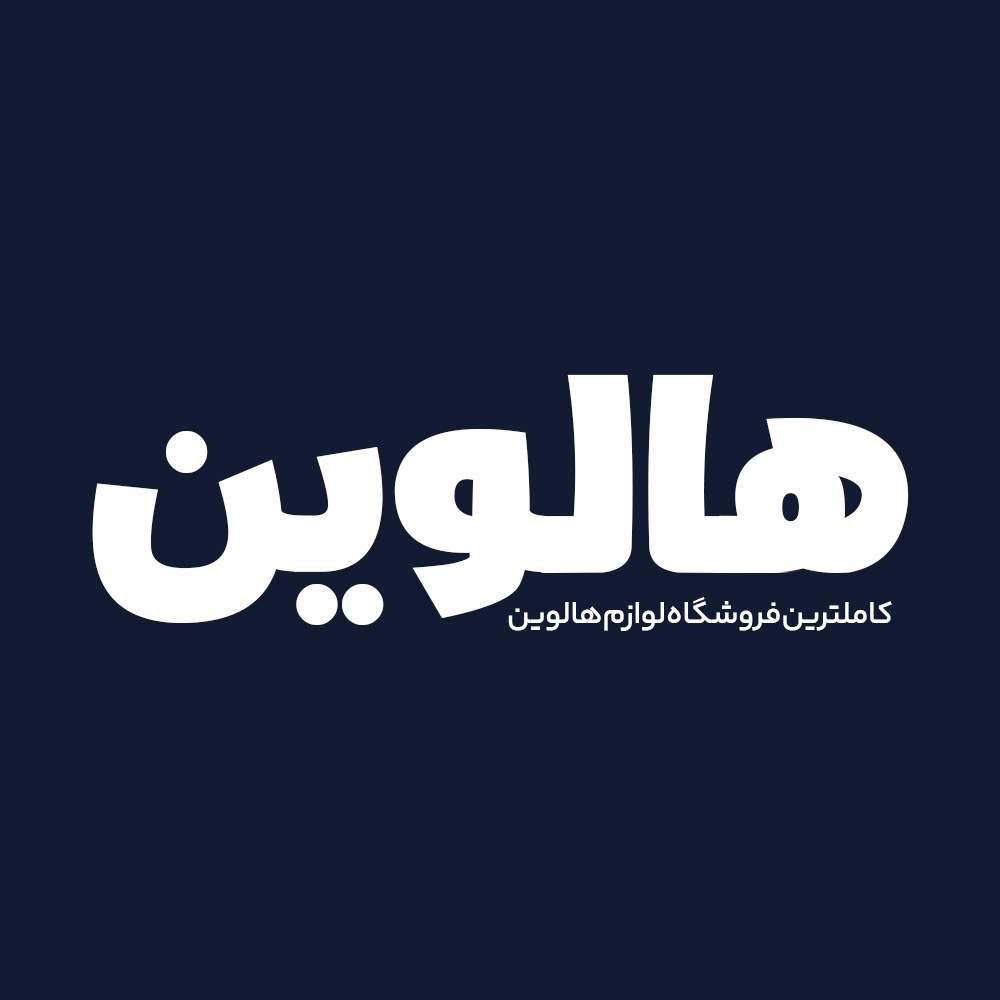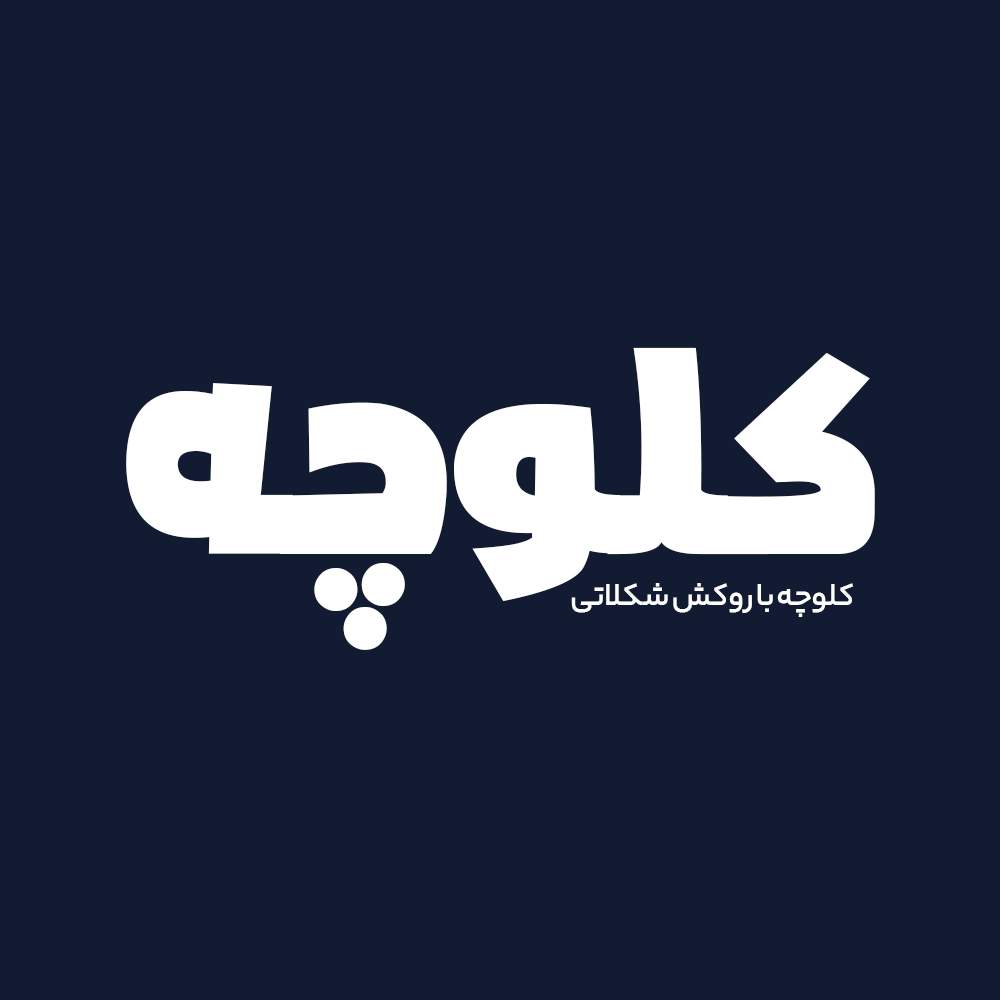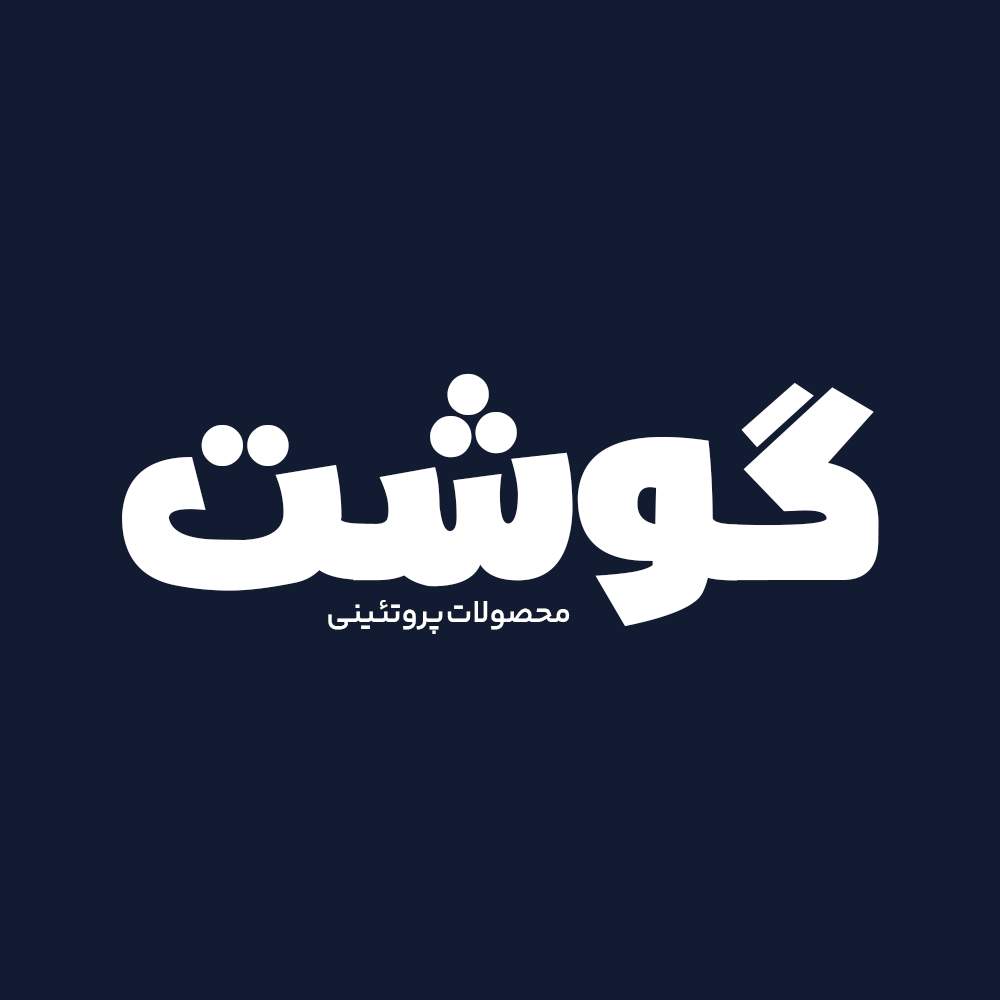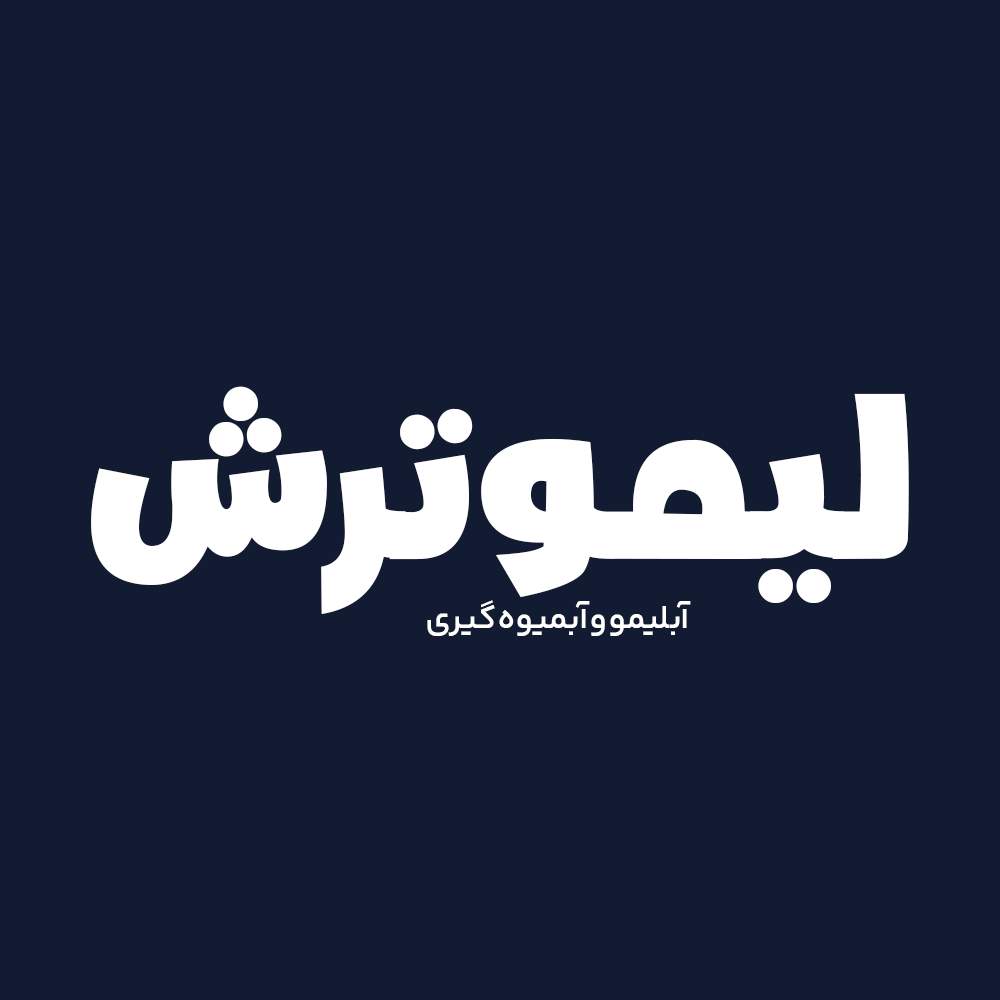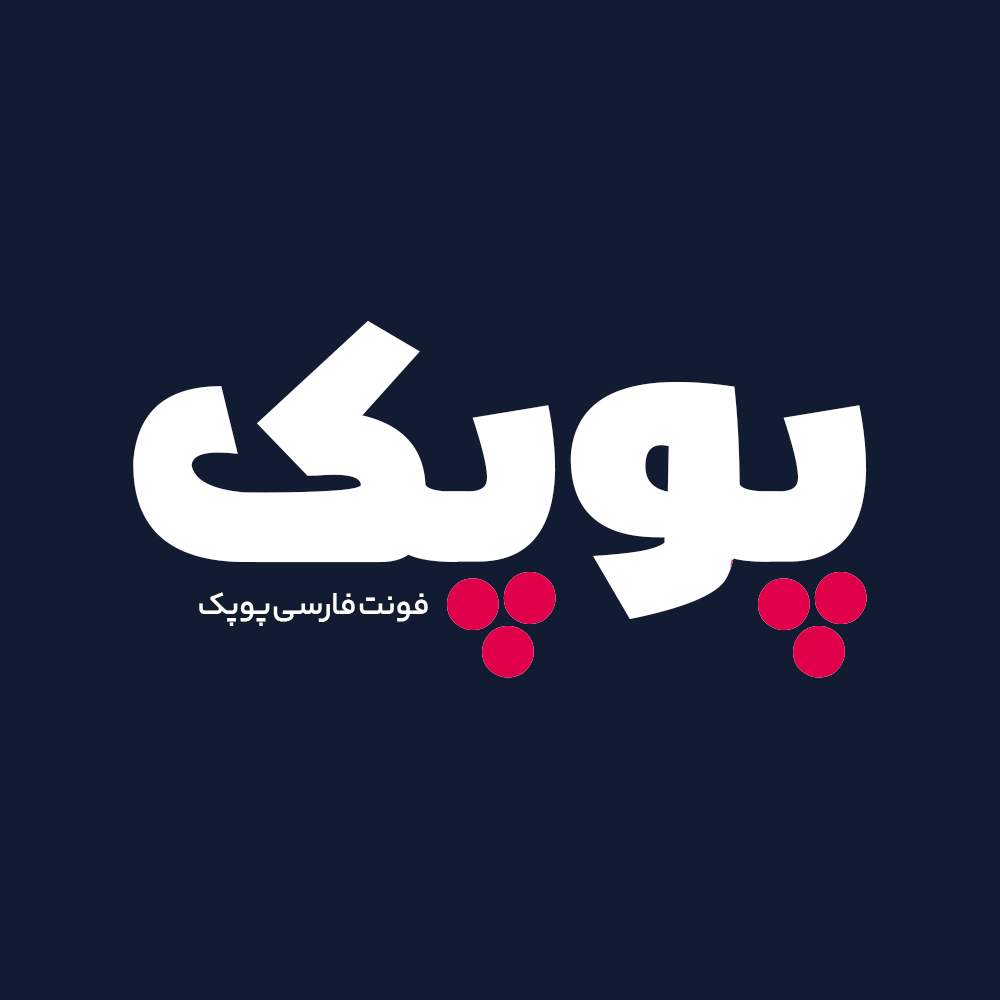
فونت فارسی پوپک Poupak Font
فونت لوگوتایپ پوپک + نسخه جدید
فونت فارسی پوپک یک فونت تک وزن با کاربرد طراحی لوگوتایپ و طراحی های مختلف همچون جلد کتاب و تولید محتوای متن های کوتاه و عناوین می باشد. این فونت با ساختار حروف خود مناسب استفاده در لوگوهای نوشتاری می باشد. همچنین از این فونت در طراحی تابلوهای چلنیوم هم به دلیل ساختار منحصر به فردش می توانید استفاده کنید. در ادامه برای شما نمونه تایپ های این محصول حرفه ای رو آماده کرده ایم که میتوانید مشاهده کنید.
در فرایند بازطراحی فونت پوپک چه کارهایی انجام شد؟
- رفع باگ های گزارش شده توسط کاربران
- بازبینی و تنظیم فاصله گذاری بین حروف
- و…
کاربرد فونت فارسی پوپک
پیشنمایش و نمونه تایپ های فونت پوپک